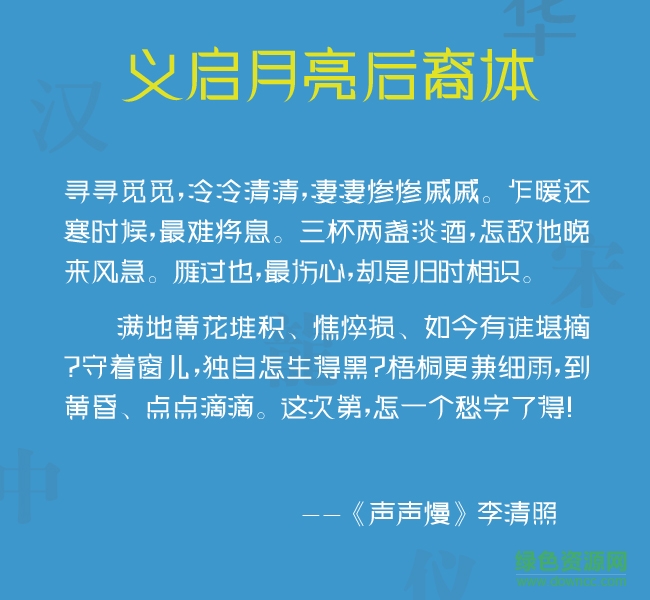
義啟月亮后裔字體是一款義啟類(lèi)可愛(ài)月亮風(fēng)格字體軟件,月亮后裔體有好幾個(gè)版本,本次小編帶來(lái)的是初始版本,優(yōu)美的弧度盡顯高貴皎潔,喜歡的朋友歡迎來(lái)綠色資源網(wǎng)下載體驗(yàn)!
來(lái)自月亮的你,月亮后裔體,就像天上的明月,沒(méi)有十五月亮的圓滿,也沒(méi)有初生月亮的纖細(xì),恰到好處的粗細(xì)給人一種恰到好處的美感。以明月之美書(shū)寫(xiě)思想之魂,使用這款字體給人一種皎潔月光下的寧?kù)o之感。